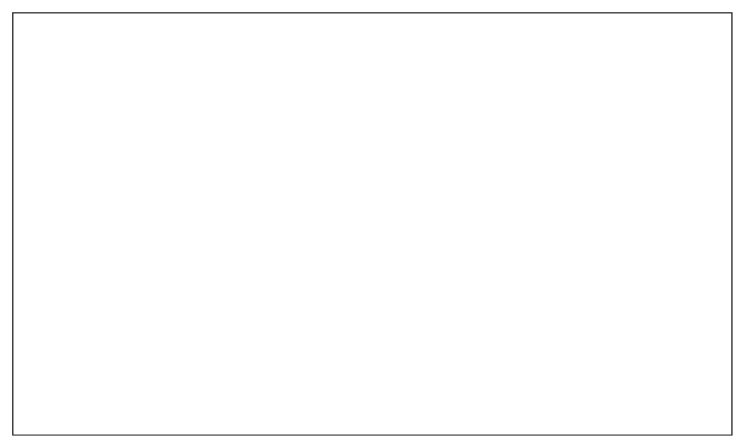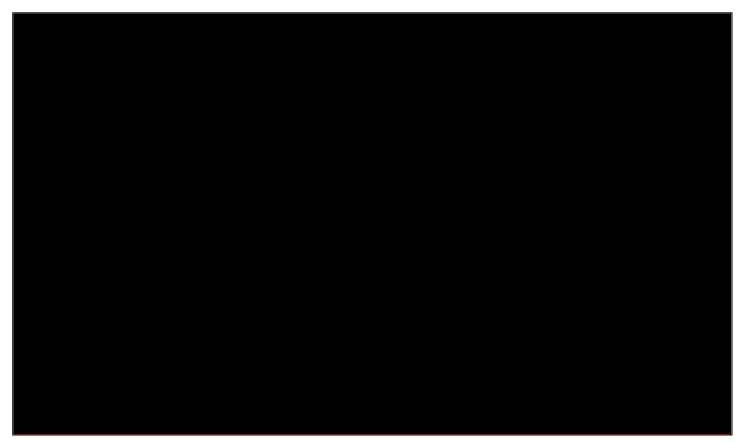
SUCHE | Fetteste Black Extended die ihr kennt
bin für ein Projekt auf der Suche nach einer richtig breiten/fetten Schrift.
Gern auch extended. Gern nicht nur SansSerif. Gern auch Slab Serif.
Gern auch Display-Schriften, nur lesbar sollte sie sein.
Da ich jetzt nicht mein ersten/naheliegendsten Einfall nehmen wollte
»Helvetica Black Extended«
zähle ich da mal auf euch ;)
Auch sehr fett zu sein scheint die Verb Condensed. Ist außerdem gerade im Angebot …
On a side note: Ich bin jetzt gerade endlich mal dazu gekommen mit der Verb und der Verb-Condesed-Familie etwas herumzuspielen. Für mich ist eindeutig die Verb Condensed die bessere Verb. Für Fließtexte läuft die Verb für meinen Geschmack viel zu weit und mit der Formensprache kann ich mich auch nicht so recht anfreunden. In der Condensed-Version hingegen finde ich sie recht ansprechend und für meinen Geschmack läßt sie sich besser lesen als die Verb.
Die Clan wäre da mein Favorit:
Übrigens: Falls einer der Herren Schriftgestalter mal einen ultrafetten Displayfont zu zeichnen gedenkt — der Name Adipositas scheint ja für einen Font bisher noch nicht vergeben zu sein.
Ich sollte auf Namensfinder für Industrieprodukte umsatteln.
der Name Adipositas scheint ja für einen Font bisher noch nicht vergeben zu sein.
Ich sehe grad eine Schriftsippe vor mir: BMI, bestehend aus eine Adipositas Sans und einer Anorexie Slab...
Hier schonmal der Entwurf für die Anorexie Slab Ultra thin:
Und Adipositas Ultra XL Vollschlank:
Keine Sorge, ich habe bisher nur Englische Texte gesetzt. Von daher ist mir diese Unförmigkeit bisher noch nicht einmal aufgefallen.
Amüsant fand ich ja auch daß Myfonts gerade ein Update der Verb Condensed angeboten hat, welches offenbar Probleme in Quark behebt, dafür die Schrift zumindest auf meinem System komplett unbrauchbar macht. Pannen kommen natürlich immer vor, aber da scheinen noch andere Dinge im Argen zu liegen.